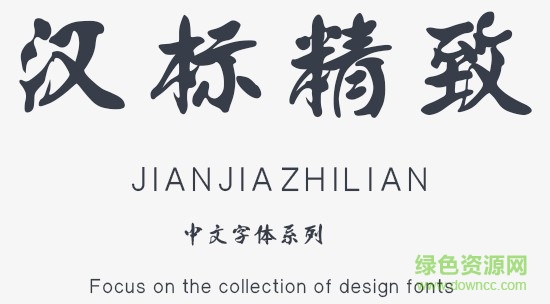
漢標(biāo)精致體是一款非常有特色的書法字體,這款字體字形粗獷飄逸,筆畫粗壯,具有古風(fēng)和藝術(shù)字體的美感,喜歡的朋友歡迎來(lái)綠色資源網(wǎng)下載使用!
漢標(biāo)精致體字體端正大方,線條簡(jiǎn)潔利落,筆鋒粗曠,帶有行楷的手寫書法風(fēng)格,是一款優(yōu)秀且耐看的中文字體。